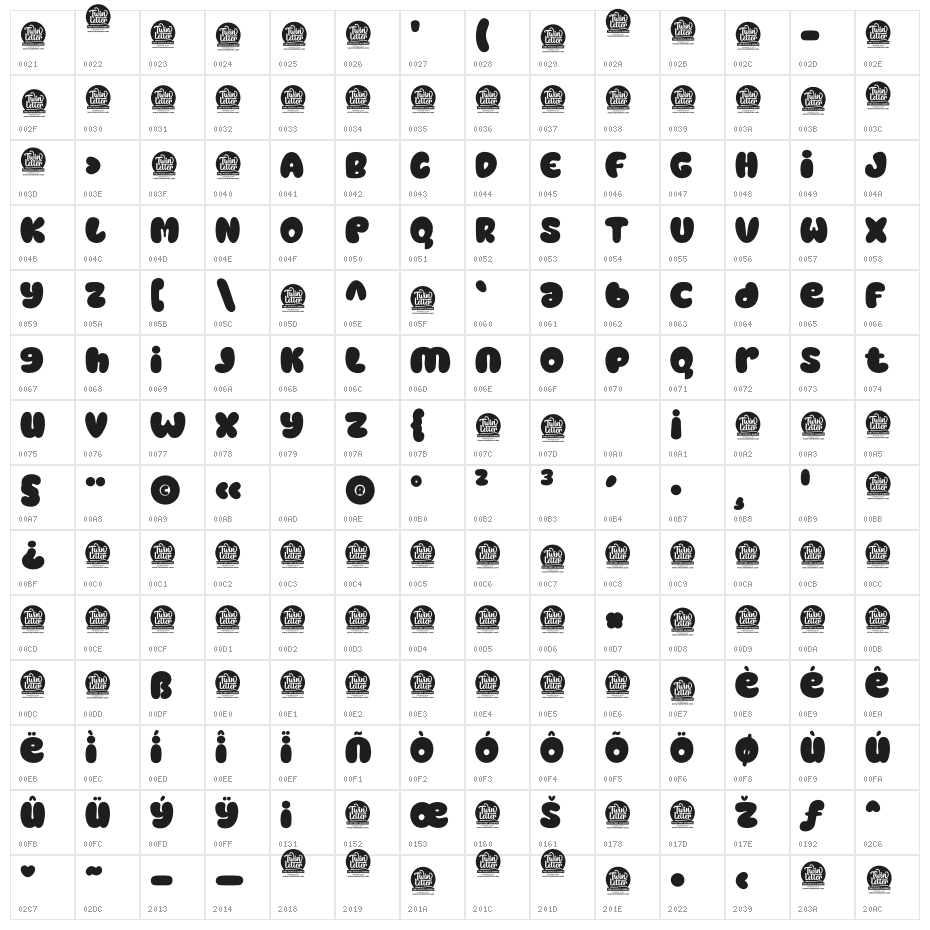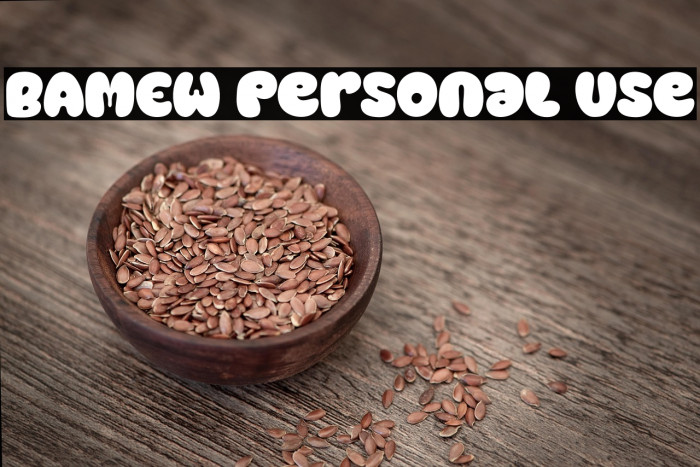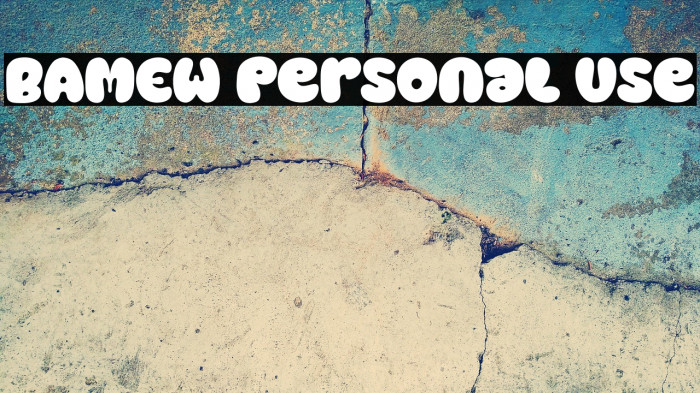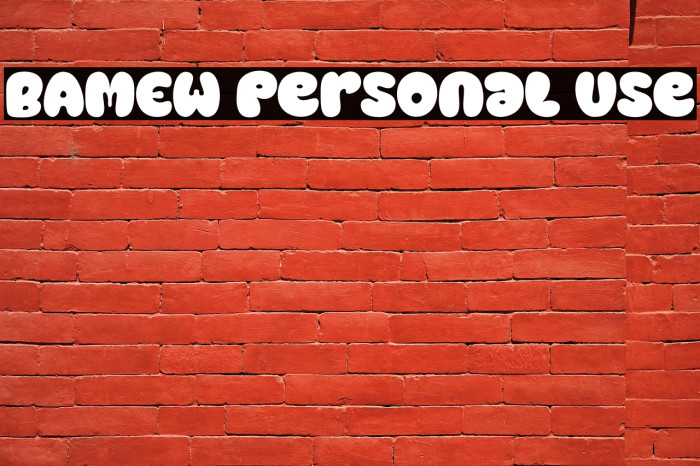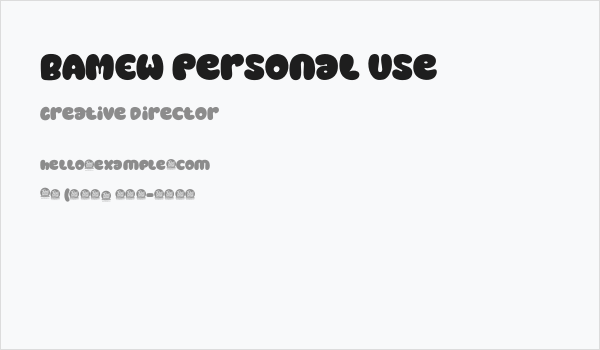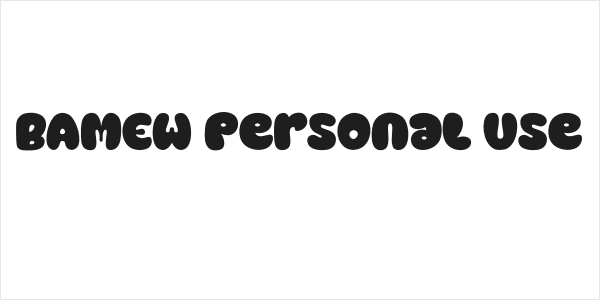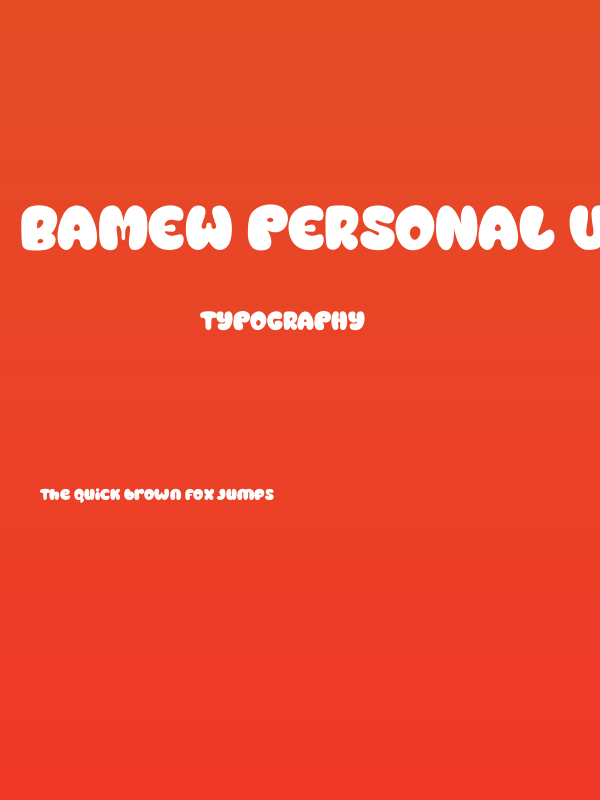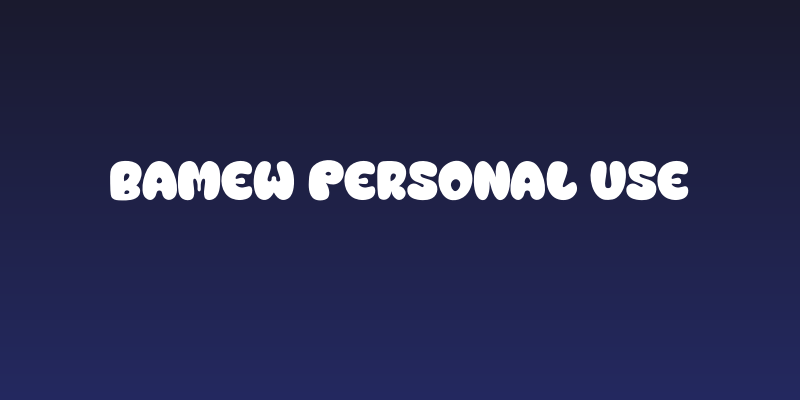
BAMEW Personal Use Font
✎ Cartoon
| 全体的なスタイル | Playful, Modern |
| おすすめプロジェクト | Ideal for children's books, playful branding, party invitations, and creative posters. |